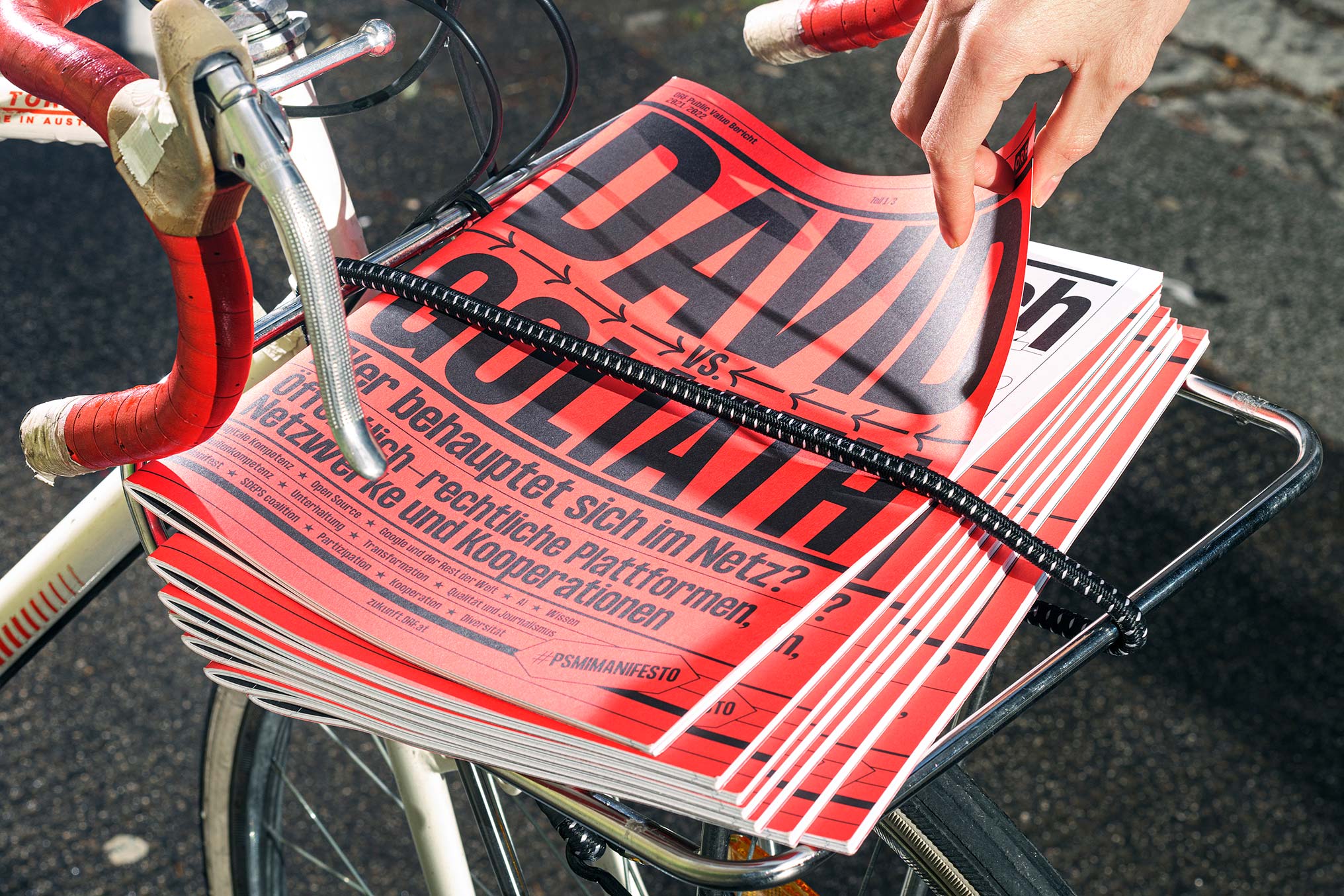
« David contre Goliath » : Qui est le vainqueur d'Internet ? La transformation numérique a déjà touché toute notre société et l'ORF (Société autrichienne de radiodiffusion), prestataire de service public et plus grand diffuseur médiatique d'Autriche, doit prendre les devants avec audace.
Avec « David contre Goliath », l’ORF présente une vision qui n’est pas un modèle économique, mais un service public : pour le public, contrôlé par le public, transparent et participatif, fiable et informatif.
« David contre Goliath » présente des articles scientifiques du monde entier, le « Manifeste du service public sur Internet » et des opinions, analyses et commentaires ORF clés qui touchent au cœur du discours médiatique d'aujourd'hui.
La mise en page s'inspire des affiches des grands combats de boxe, mettant en scène le rapport comme un combat « David contre Goliath ». Des éléments facilement reconnaissables parcourent l'ensemble de la publication, guidant le regard du lecteur et structurant le contenu. Ludique, mais clair et net, le texte présente des scientifiques et des experts qui montent sur le ring dans une série de portraits dynamiques. Les couleurs se limitent au rouge et au noir, créant une image globale épurée où le contenu dicte la mise en page.